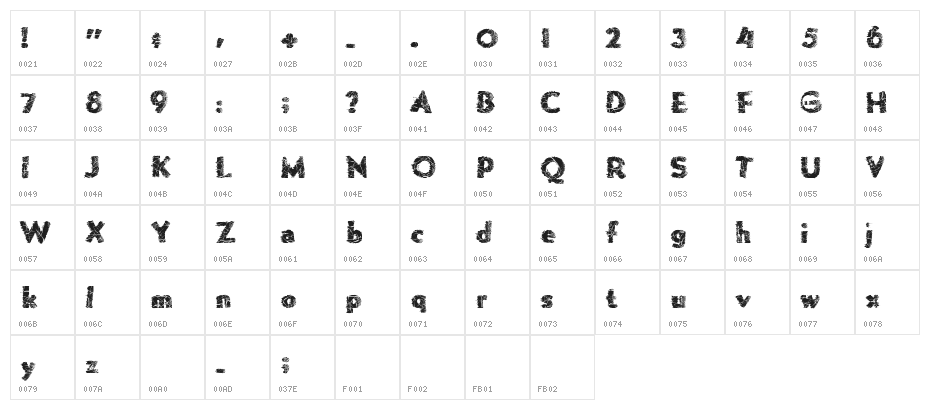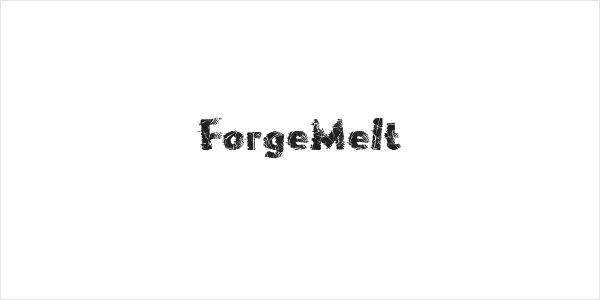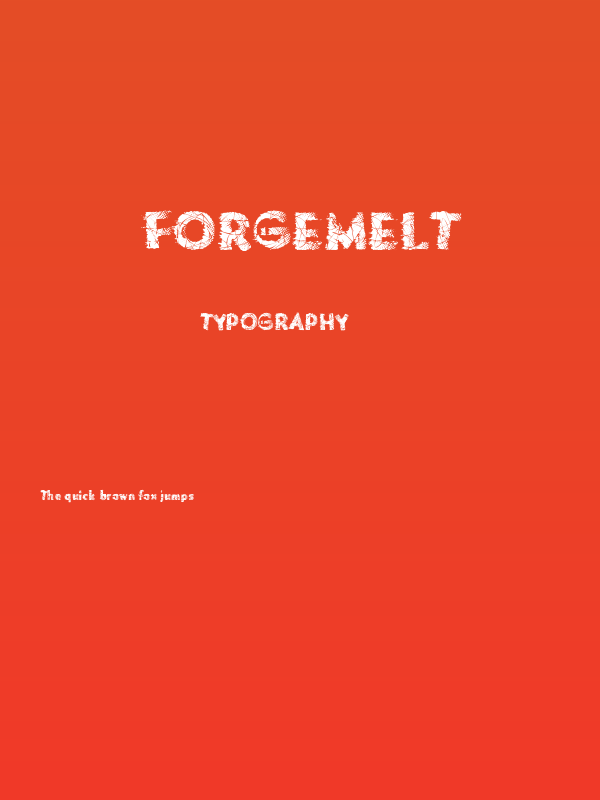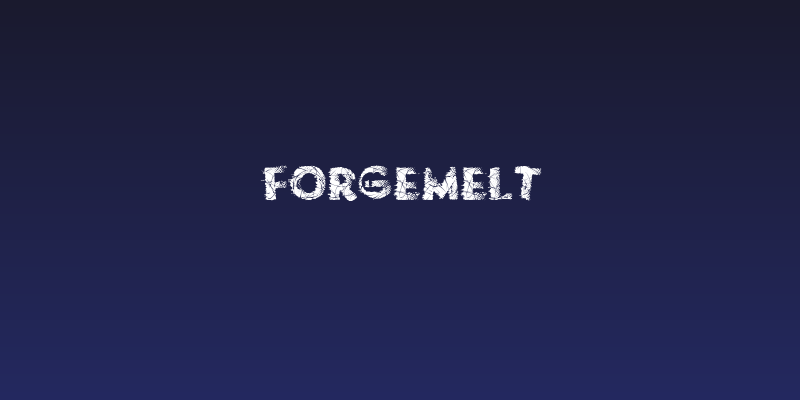
ForgeMelt Font
✎ Distorted Eroded
Fonts by Xerographer Fonts
| Categorie | Distorted Eroded |
| Stile generale | Modern, Edgy |
| Progetti proposti | Ideal for posters, album covers, branding for edgy products, and artistic projects. |